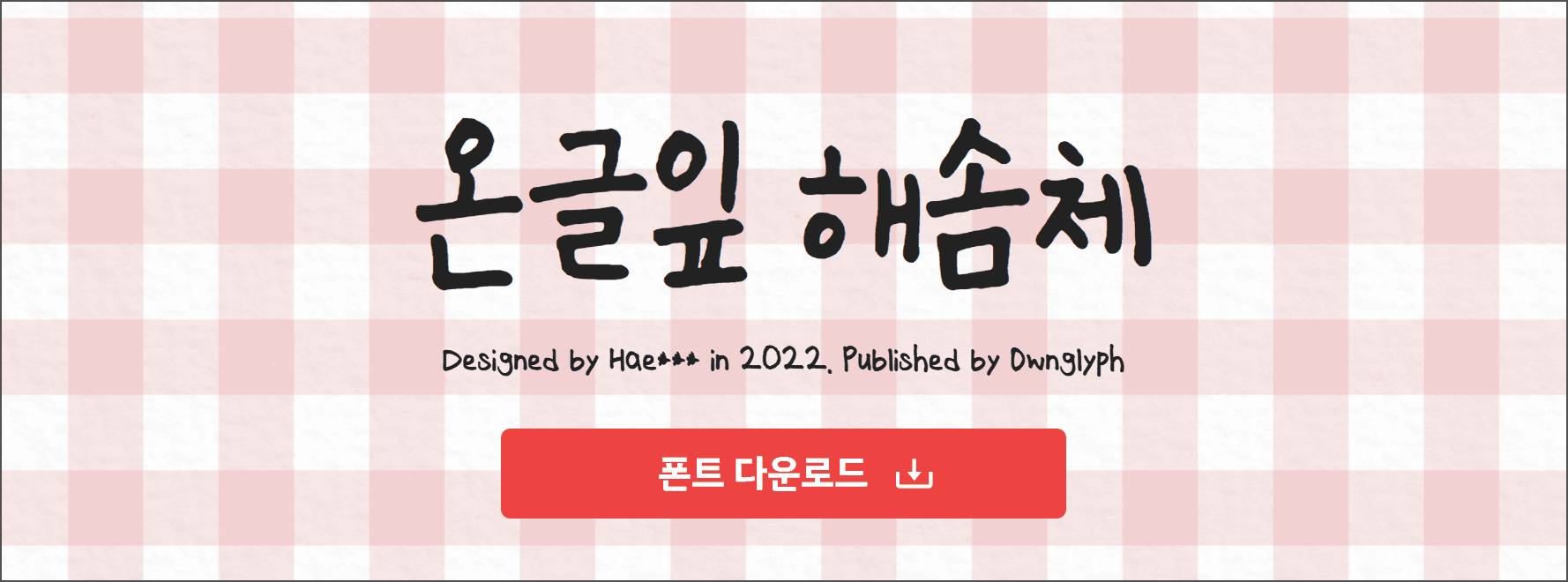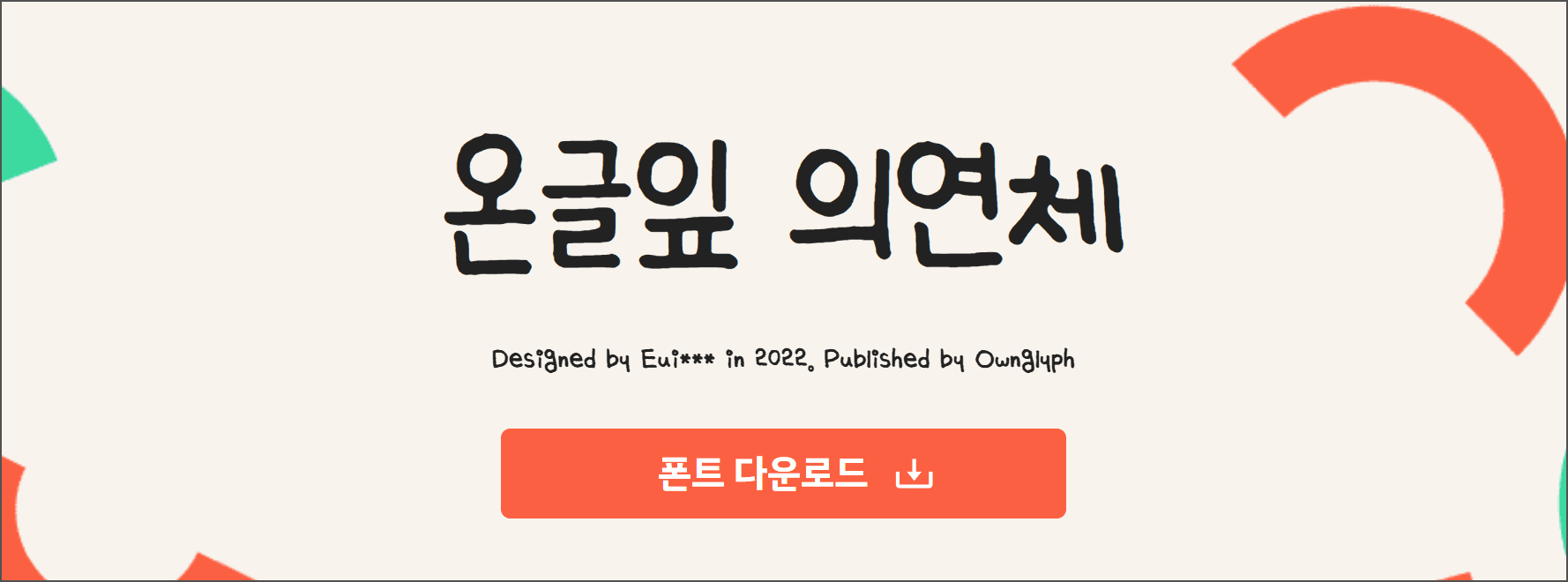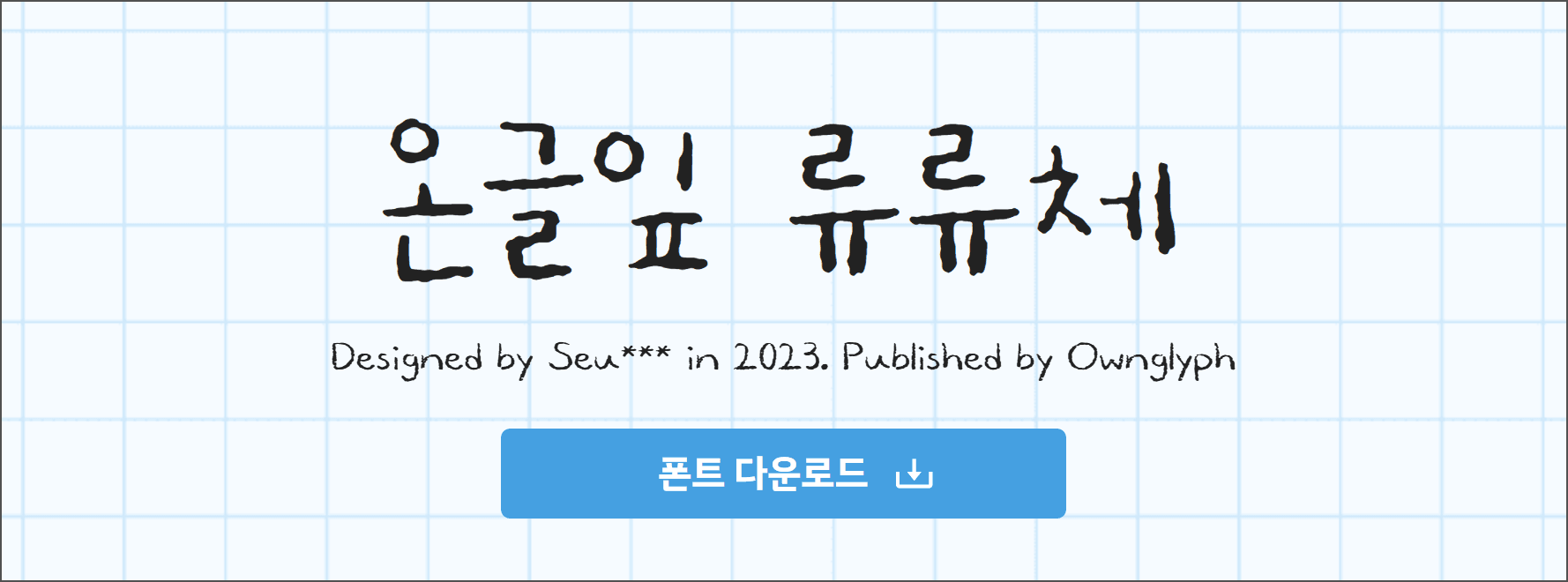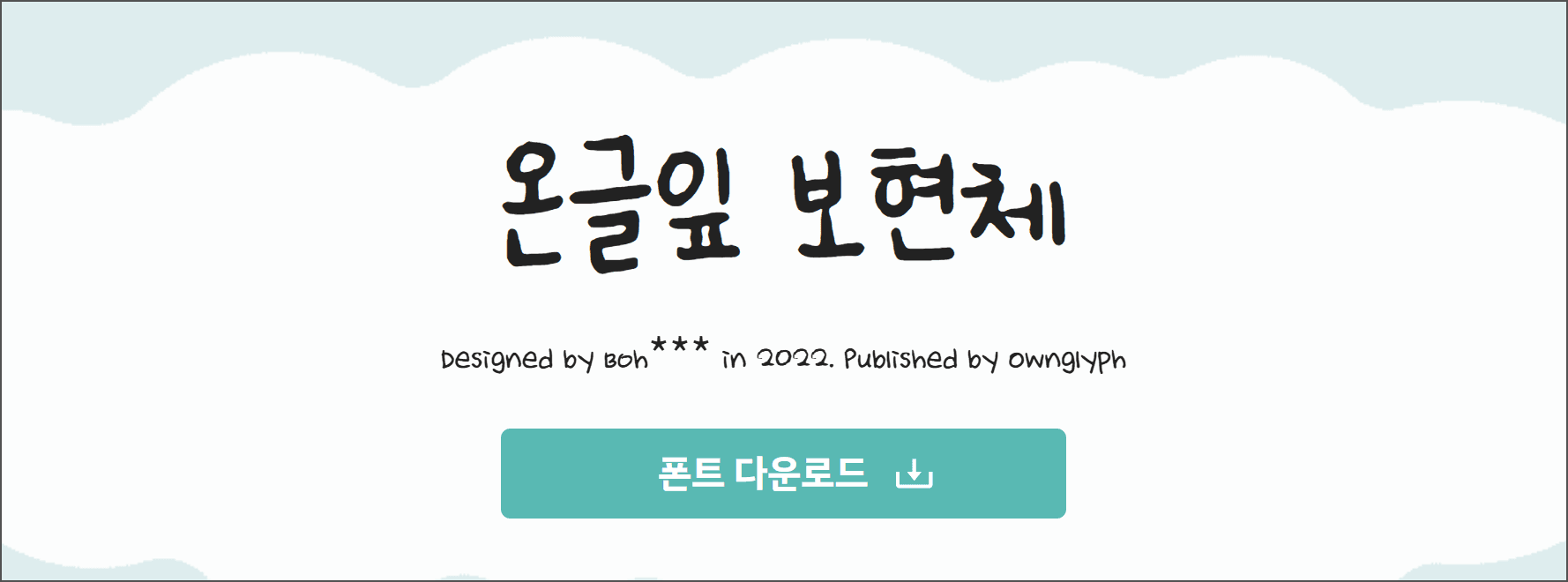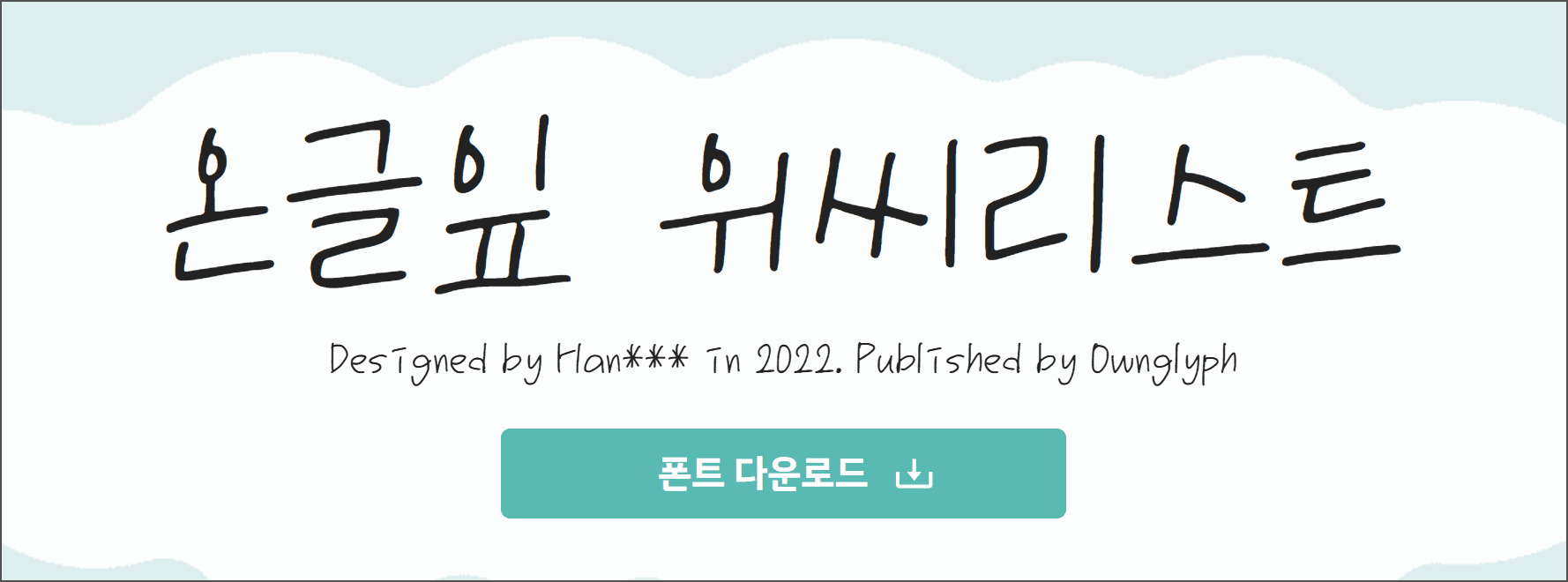
온글잎 폰트란? 신규 제작은 끝났지만 기존 폰트는 계속 받을 수 있다
온글잎(Ownglyph)은 인공지능 스타트업 (주)보이저엑스가 만든 디지털 손글씨 폰트 플랫폼입니다. 과거에는 서체 하나를 만들기 위해 폰트 디자이너가 수천 자의 한글 자모를 일일이 그려야 했습니다. 하지만 온글잎은 사용자가 직접 쓴 몇 백 자의 손글씨 데이터만 입력하면, 딥러닝 알고리즘이 필체의 특징(기울기, 굵기, 자간, 획의 삐침 등)을 학습하여 11,172자의 모든 한글 글꼴을 완성된 디지털 벡터 데이터로 구현하는 기술을 선보였습니다. 그 결과 전문 디자이너가 아닌 일반인들의 개성 있는 실제 손글씨들이 대거 무료 폰트로 배포될 수 있었습니다.
실무자가 꼽은 가독성 좋은 온글잎 폰트 BEST 5
온글잎 폰트 중 실무에서 활용도가 높고 독자 반응이 좋았던 가독성 뛰어난 폰트 5가지를 소개합니다. 각 폰트 페이지는 온글잎 공식 사이트에서 직접 확인할 수 있습니다.
온글잎 해솜체: 또박또박 정성 들여 쓴 어른의 손글씨 느낌이 물씬 풍깁니다. 가독성이 매우 뛰어나 정보 전달이 주가 되는 블로그 본문이나 정보성 카드뉴스에 잘 어울립니다.
온글잎 의연체: 고딕체 특유의 단단함과 손글씨의 부드러움이 절묘하게 섞여 있습니다. 예능 자막이나 여행 콘텐츠의 제목용으로 많이 쓰입니다.
온글잎 류류체: 둥글둥글하고 귀여운 색연필 감성이 돋보이는 폰트입니다. 브이로그 영상에서 화자의 속마음을 텍스트로 띄울 때나 다이어리 꾸미기에 잘 어울립니다.
온글잎 위씨리스트: 캘리그라피 펜으로 힘을 주어 쓴 듯한 역동성이 특징입니다. 명언 인용이나 포스터 메인 카피, 감동적인 영상의 오프닝·엔딩 크레딧에 사용하면 글에 생명력을 불어넣을 수 있습니다.
온글잎 보현체: 군더더기 없이 깔끔하고 모던한 손글씨입니다. 너무 감성적이거나 유치하지 않아 회사 내부 발표용 PPT나 진지한 칼럼의 소제목으로 활용하기에 안성맞춤입니다.
산돌구름은 클라우드 서비스라 폰트 파일을 직접 제공하지 않습니다. 산돌구름 앱을 설치하고 폰트를 활성화하는 방식으로 사용하며, 폰트 파일이 필요한 임베딩 서비스는 이용 목적에 맞는 별도 구매계약이 필요합니다. 또한 무료 체험용 “스타터팩은 비상업적 용도로만 사용해야 합니다”라는 공식 안내가 있으니, 상업 프로젝트에는 스타터팩이 아닌 무료폰트(폰트별 범위 확인) 또는 정식 상품을 사용하세요. 산돌구름 공식 무료폰트 안내에서도 “무료로 제공되는 폰트라도 폰트별로 사용 범위가 다를 수 있고, 라이선스는 중간에 변경될 수도 있다”고 명시하고 있습니다.
툴디는 기존 글에서 다운로드 사이트처럼 소개됐지만, 실제로는 폰트 추천 매거진과 웹 디자인 에디터 서비스입니다. 툴디 자체가 폰트 파일을 배포하거나 자체 라이선스를 정하는 배포처가 아니므로, 툴디 글에서 소개된 폰트를 쓸 때는 해당 폰트의 원 배포처 라이선스를 확인해야 합니다. 에디터 안에서 카드뉴스·썸네일을 만들 때 폰트를 활용하는 용도와, 폰트 파일을 받아 다른 곳에 쓰는 용도는 다릅니다.
목적별 무료 폰트 다운로드 사이트 추천
각 사이트마다 장단점이 명확하므로 작업 환경에 맞춰 선택하세요.
1눈누 — 미리 써보고 받는 것이 목적일 때
국내 최대 상업용 무료 폰트 집합소입니다. 온글잎에서 제작된 수십, 수백 종의 폰트가 눈누에 등록되어 있습니다. 다운로드 전에 원하는 텍스트를 입력해 보는 “미리 써보기” 기능으로 내 디자인에 어울리는지 바로 확인할 수 있어 불필요한 폰트 설치를 막아줍니다. 단, 폰트별 라이선스 요약표를 반드시 확인하세요.
2산돌구름 — 파일 설치 없이 여러 PC에서 동기화할 때
폰트 파일을 일일이 설치하는 것이 번거롭다면 산돌구름이 편리합니다. PC 앱을 설치하면 클릭 한 번으로 폰트가 활성화되고, 프리미어 프로 등 다양한 프로그램에서 바로 쓸 수 있습니다. 다만 파일 자체를 받지 못하므로 웹폰트·기기 임베딩이 필요하면 별도 문의가 필요하고, 스타터팩은 비상업적 용도만 가능하다는 점을 기억하세요.
3툴디 — 폰트 조합 영감을 얻고 에디터에서 바로 만들 때